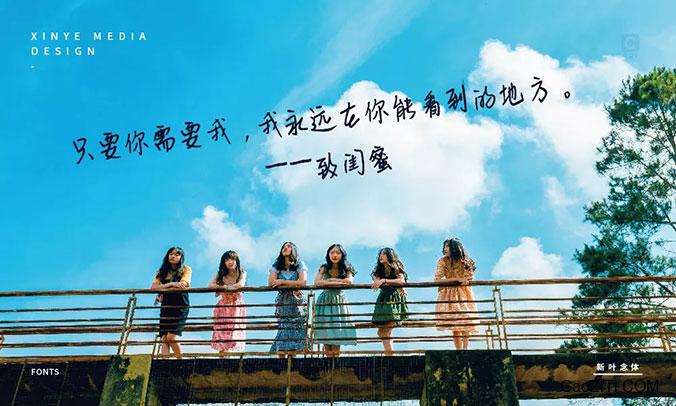
新叶恋体
新叶传媒出品,手写字体,有着强烈的人文气息
字体介绍
名称来源:念是惦记,是想念,是思念,是牵挂。手写字有着强烈的人文气息,不管身在何处,请告诉远在家乡的父母,我很好;不管彼此离的有多近,请告诉你的那个TA,我爱你!纸短情长,见字如面
项目顾问:乔建;设计与开发指导:袁立、王亚; 手写作者:李雨; 小组成员:秦园园